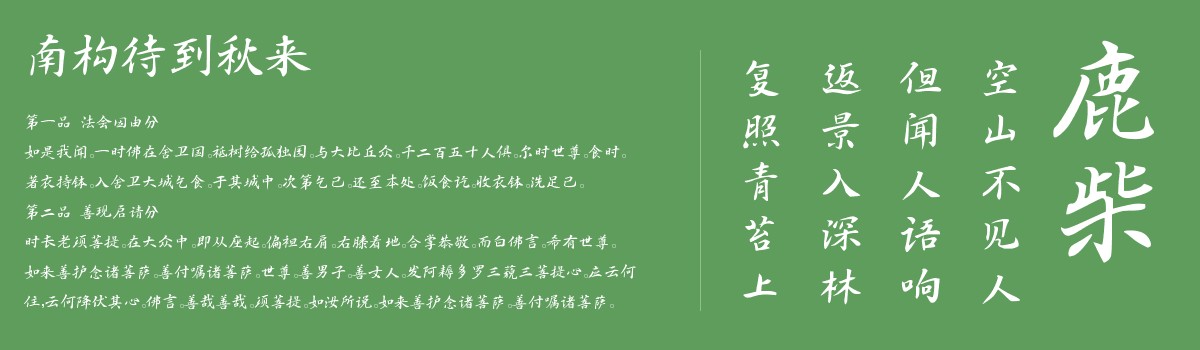
南构待到秋来
南构待到秋来是一款艺术字体,此字体笔画兼具书法韵味与手写温度:起笔多有顿挫,似毛笔侧锋轻切入纸,收笔轻提带露锋,利落中藏灵动。横画平稳略向右上微倾,如扁担承力;竖画挺拔如孤松,中段略收显骨感。撇捺舒展若羽翼,末端稍扬带飘逸,折角处方圆相济,方折见刚劲,圆转显柔和。结构疏密有度,部件穿插自然,重心沉稳却不失活泼,整体似行云流水一气呵成,透着书卷气与手写的亲切感。比较适合用于艺术类装饰文字,海报、网页、广告设计,室内装饰,平面标题设计、食品包装、品牌标志等。